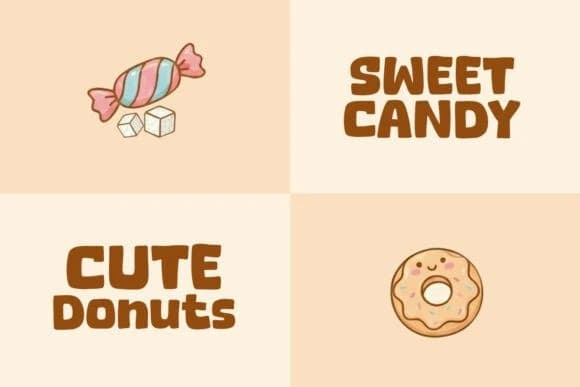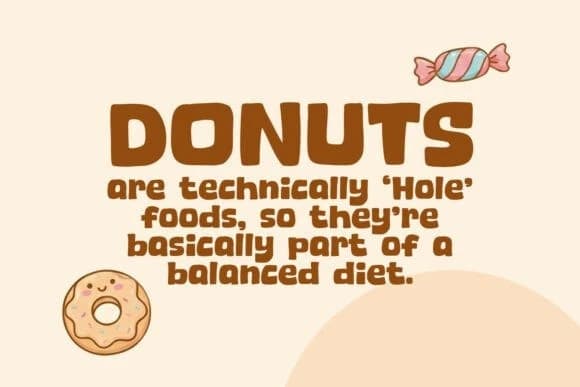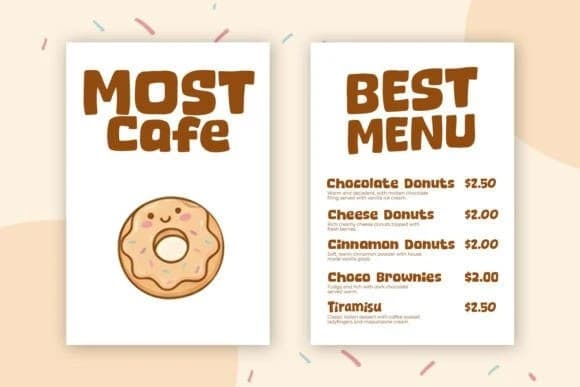
Sweet Tone Yazı Tipi
Sweet Tone Font, posterler, logolar, dergiler, kitap kapakları, afişler ve çok daha fazlası için mükemmel, modern ve sevimli bir sergileme yazı tipi! Bu harika fontu edinin ve hoş tasarımlar yaratmak için kullanın! İnanılmaz derecede geniş bir proje yelpazesine kolayca uyum sağlar.
Sweet Tone Font, posterler, logolar, dergiler, kitap kapakları, afişler ve çok daha fazlası için mükemmel bir modern ve sevimli gösterim yazı tipidir! Bu harika fontu edinin ve güzel tasarımlar yaratmak için kullanın. Oldukça geniş bir proje yelpazesine kolayca uyum sağlayabilir
Sweet Tone